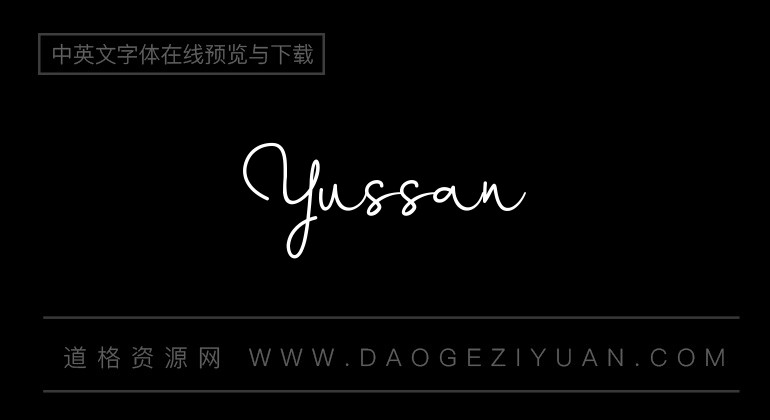
Yussan 字体是一种源自日本的日文草书字体,由日本设计师Yussan创作。它的特点是自然、柔和,细节十分精致,具有流畅的线条,曲线舒缓,字体宽度较宽,比较有温暖感。它能够带给人们一种轻松的感觉,使得文字看起来更加舒服。内容介绍
Yussan是一款非常不错的手写艺术字体,具有很好的视觉感,适合于文化类的宣传设计、商业类品牌的广告和产品包装设计以及个性化文字排版等较多场景。